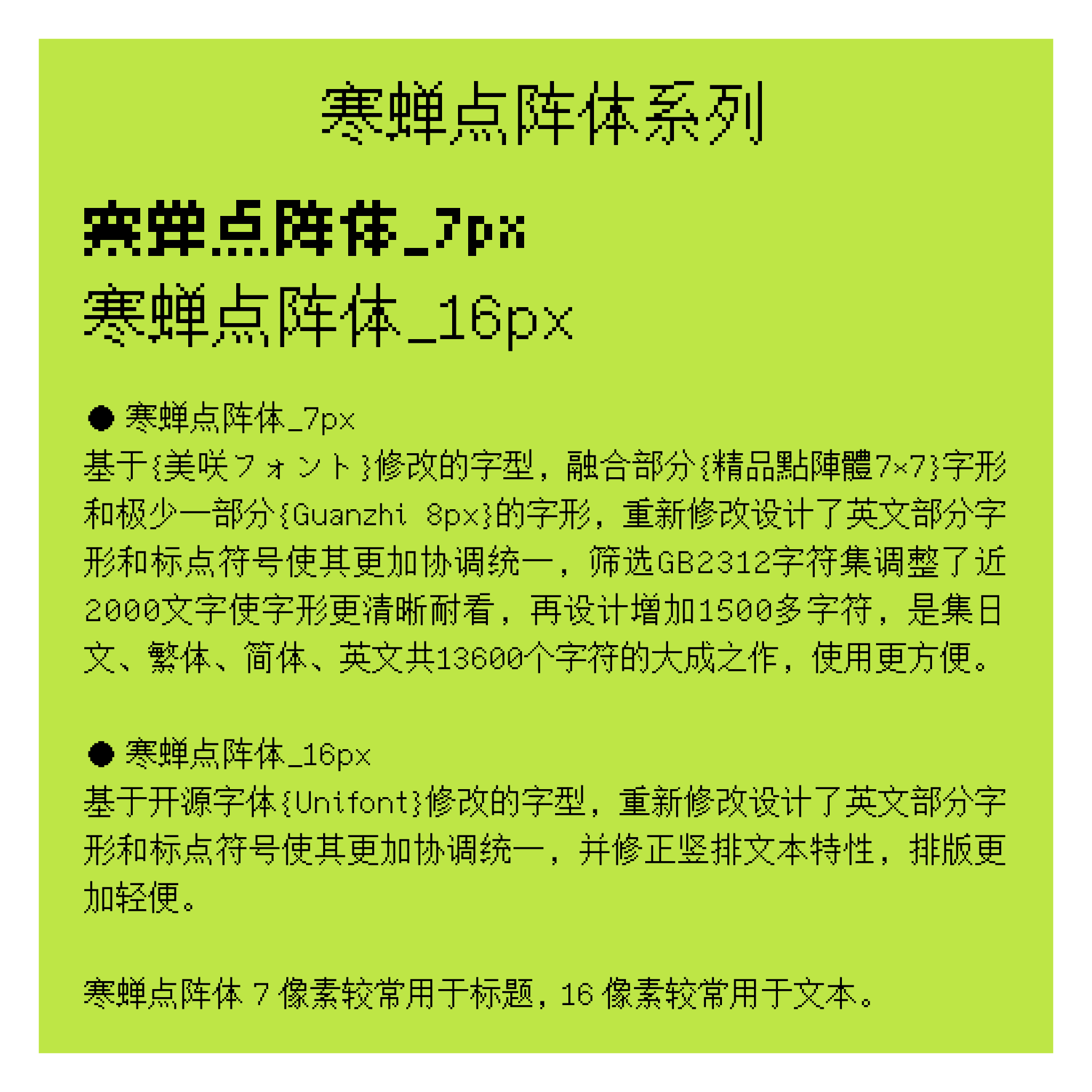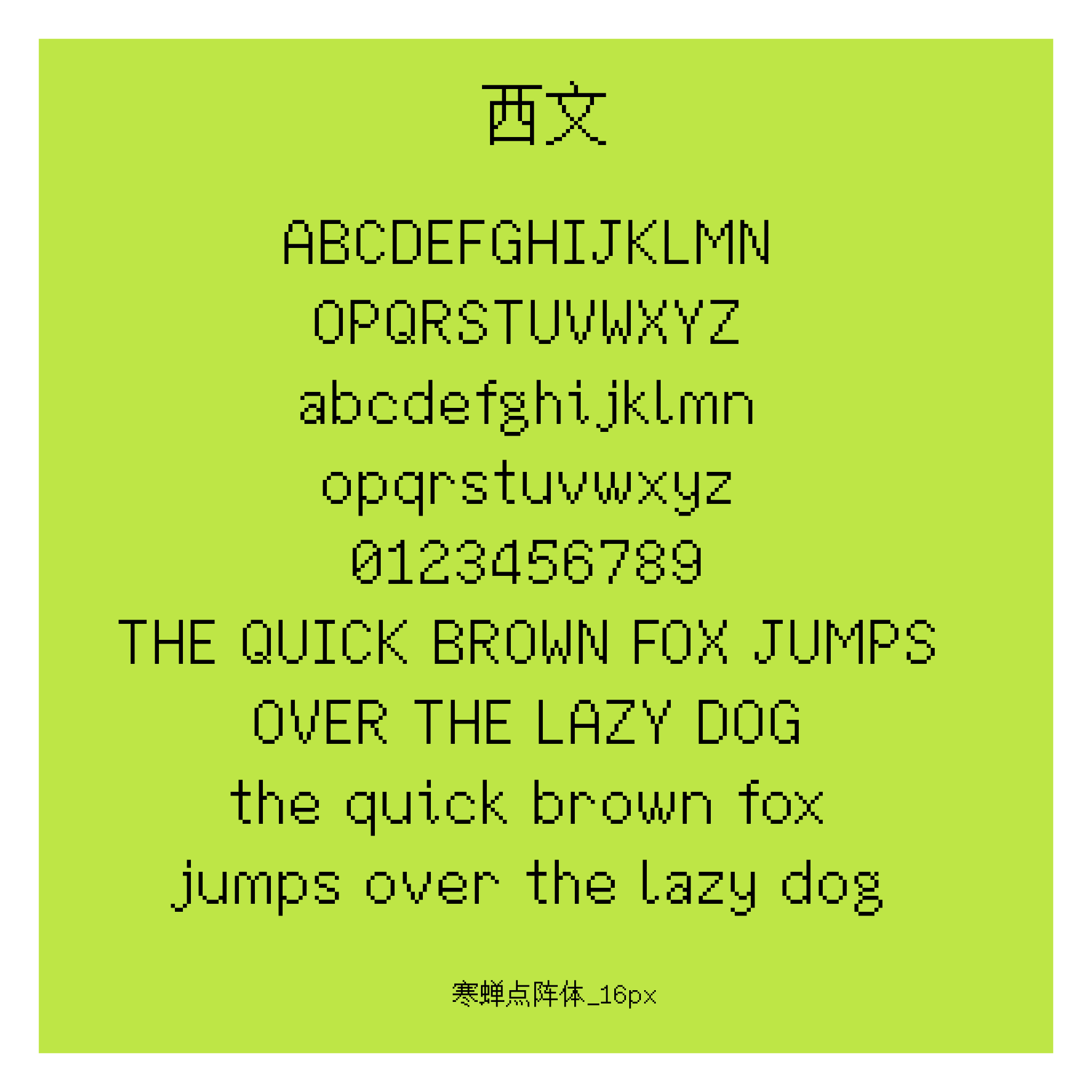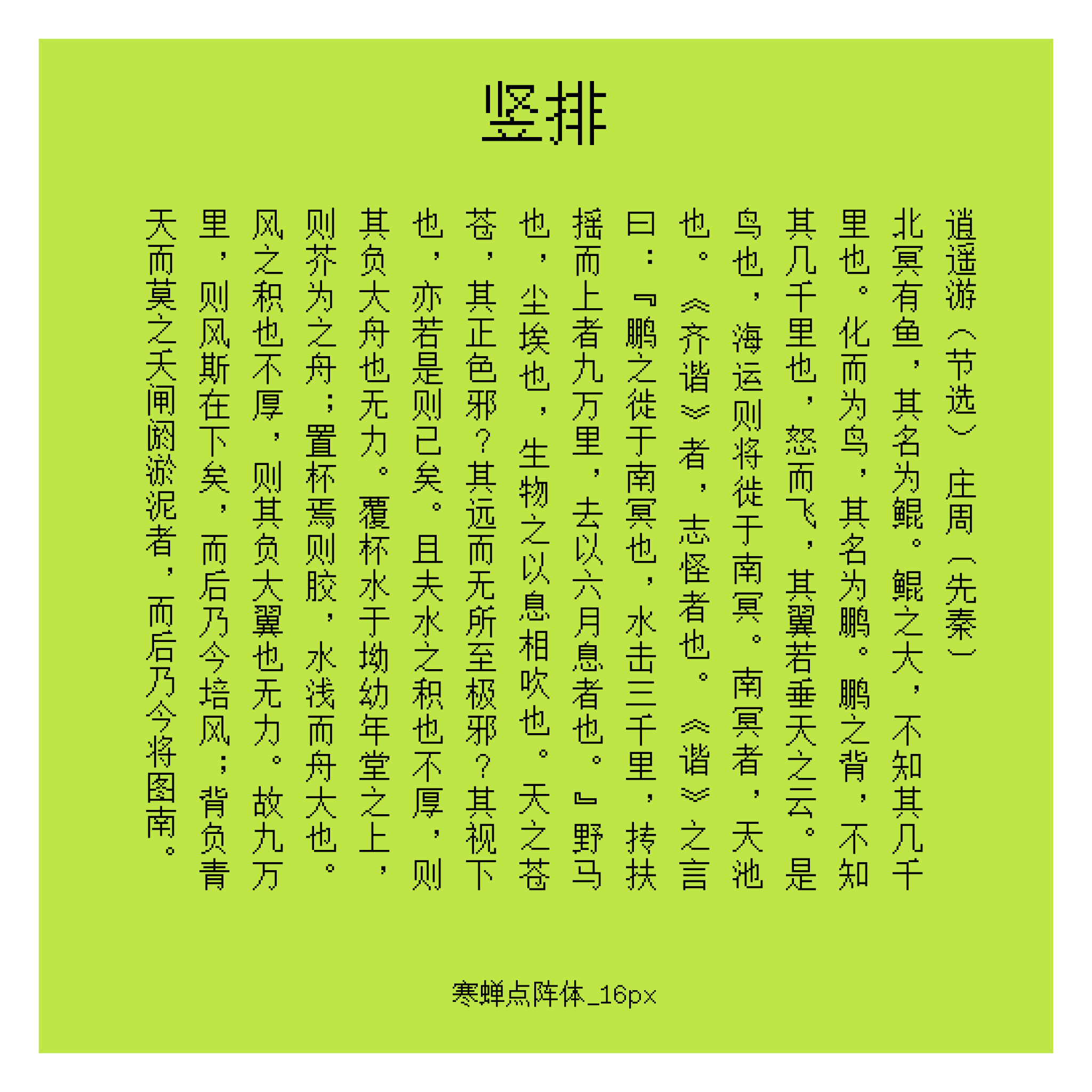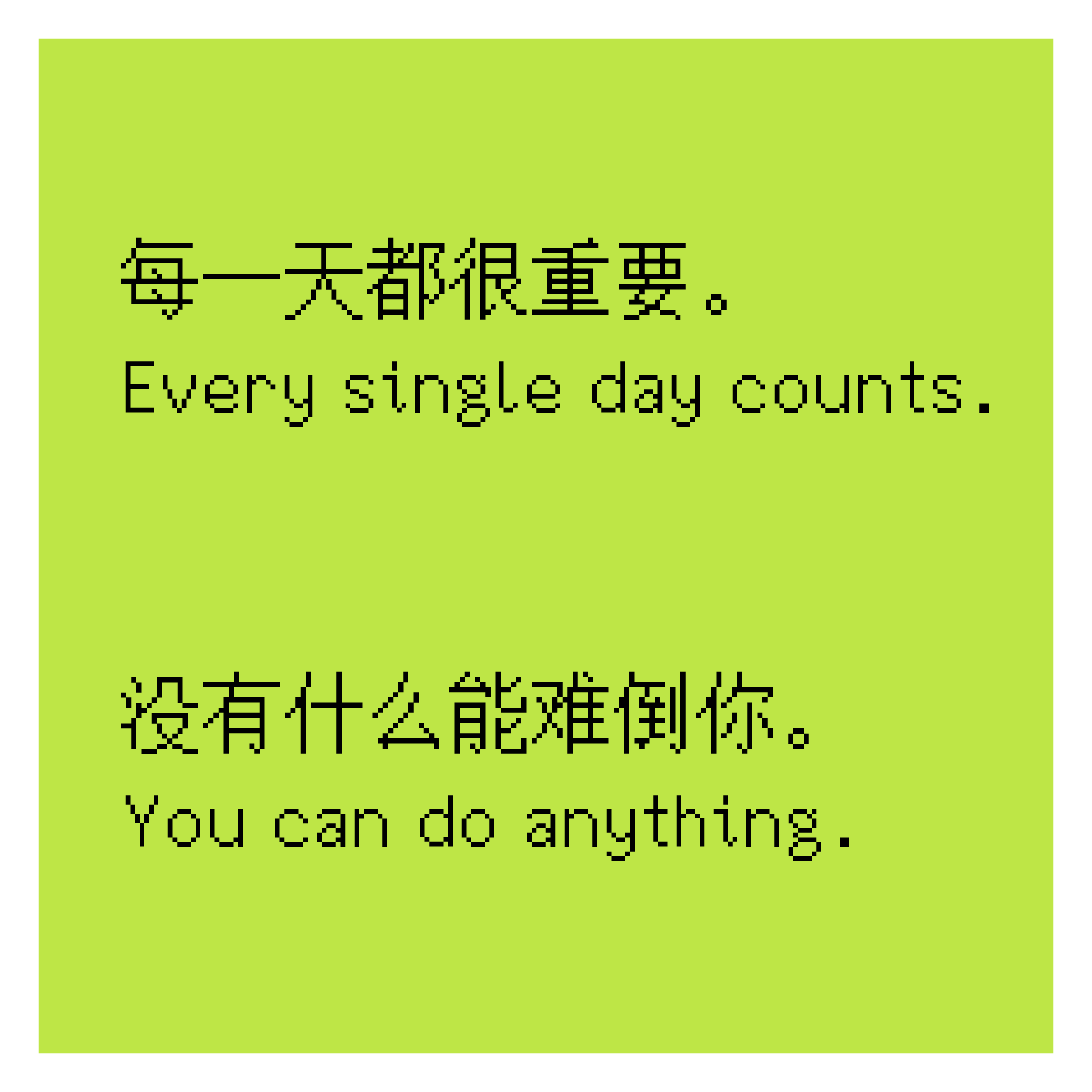
寒蝉点阵体_16px
基于开源字体{Unifont}进行二次创作与优化的字体设计,重点针对英文字符及标点符号的字形进行了全面重构与精心调整,旨在提升整体排版的视觉协调性与风格统一性。设计师在保留原有字体核心特征的基础上,对英文字母的比例、笔画细节以及标点符号的形态与位置进行了细致打磨,使其在与中文混排时能呈现出更和谐、连贯的视觉效果。同时,本版本特别修正并增强了对竖排文本的支持,优化了字符的间距与基线对齐,确保在垂直排版场景中字符能自然排列、阅读流畅。此外,通过调整字体的度量参数与轮廓精简,在保持清晰可读性的前提下,实现了更为轻盈、紧凑的排版效果,尤其适合于空间受限或需要高密度信息呈现的版面设计。这些改进共同使得该字体在各类现代排版应用中具备更强的适应性与美学表现。